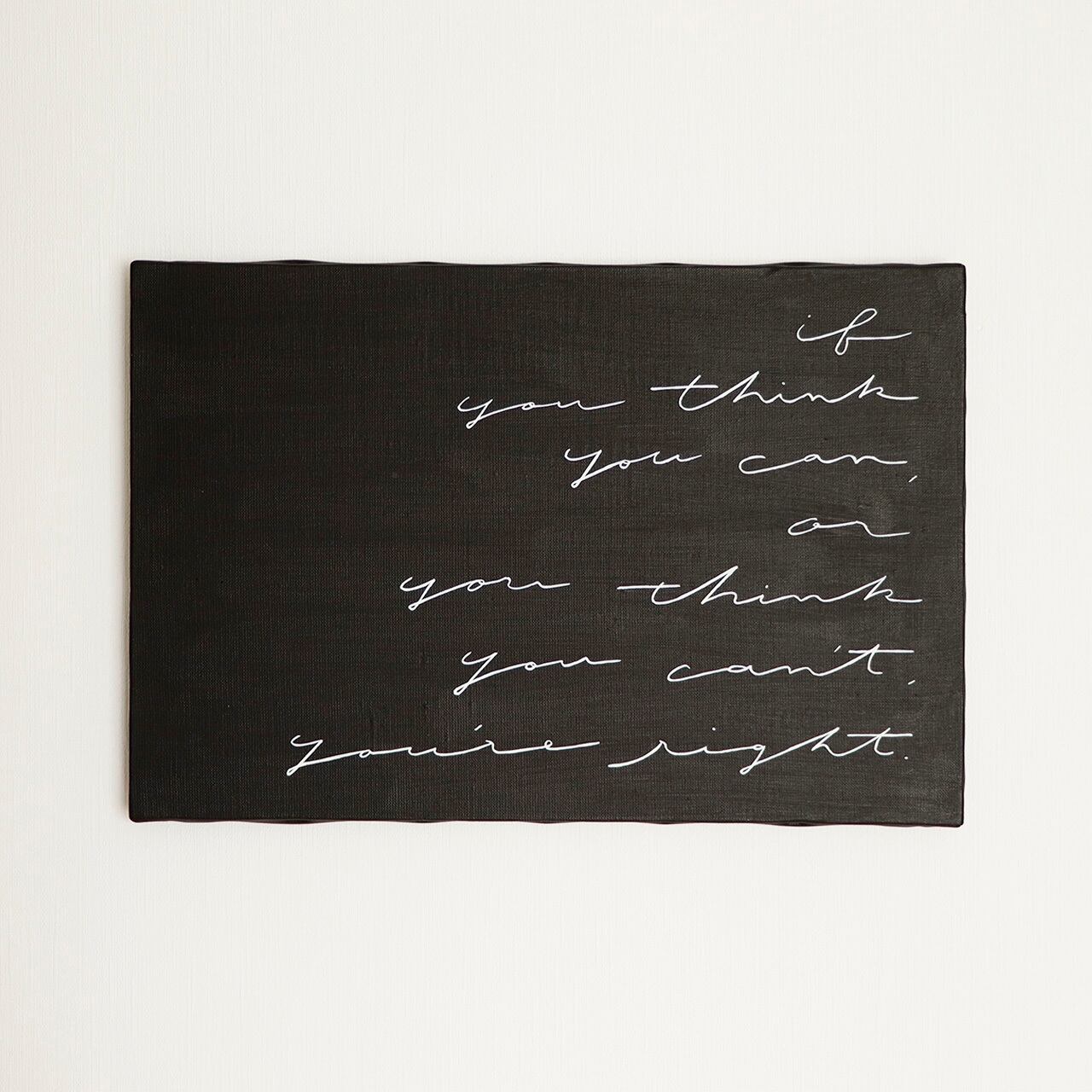
if you think you can, or you think you can’t you’re right
できると思えば可能だし、できないと思えば不可能だ
挑戦したい時、自分を鼓舞してくれるような言葉を描きました。
内に秘めている雰囲気を出したくて、真っ黒な背景と白い文字に。
この作品で、見る人の気持ちがちょっとだけでもポジティブになれば嬉しいです^^